예쁜 글씨체 폰트 검색방법... 산돌구름에서 이미지로 글씨체 확인!!
오늘은 인터넷에서 예쁜 글씨체를 발견했을 때 폰트 이름을 검색하는 방법에 대해서 알아볼게요. 그럼 지금부터 바로 시작해 보겠습니다. 산돌 구름 홈페이지에서 이미지로 글씨체를 확인하는 방법이 있습니다.
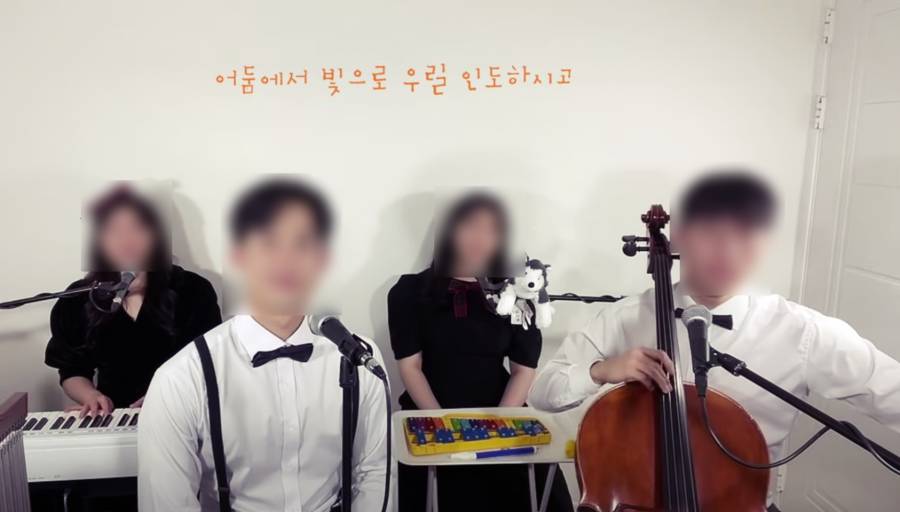
제가 좋아하는 유튜브 채널에서 CCM을 시청하고 있었는데요. 그 노랫말, 가사 글씨가 너무 예쁜 거예요. 갑자기 글씨체, 글꼴이 궁금해졌답니다. 대체 무슨 폰트일까? 호기심이 발동!!! 일단 전체화면을 캡처해 보았습니다.ㅎㅎ
그러고 나서 바로 산돌구름 홈페이지에 접속해 봅니다... 산돌구름 홈 화면 상단 우측에 보면 '키워드나 이미지로' 폰트 검색하는 방법이 있답니다.ㅎㅎ
산돌구름 홈페이지에서 이미지로 폰트 검색을 눌러봅니다...
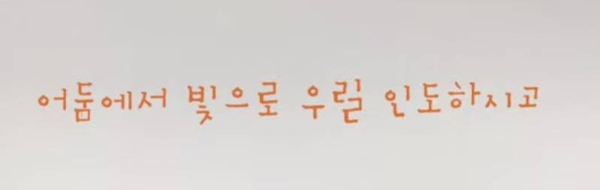
미리 캡처화면에서 글씨들만 따로 편집해 두었답니다.ㅎㅎ 정말 산뜻하고 예쁜 글씨체입니다... 얼른 글씨체 이름을 알고 싶네요.
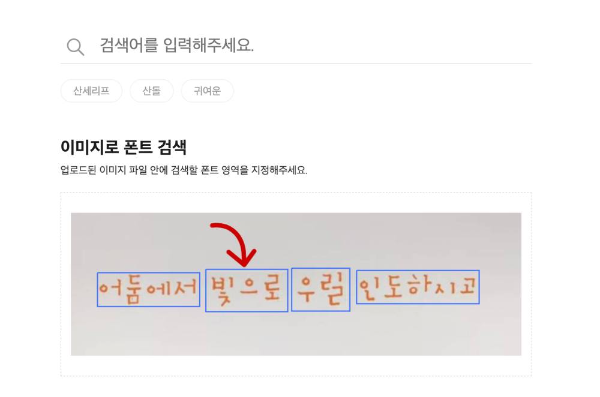
이미지로 폰트 검색에서 검색할 폰트 영역을 지정해 줍니다. 저는 '빛으로' 영역을 클릭해 주었습니다...
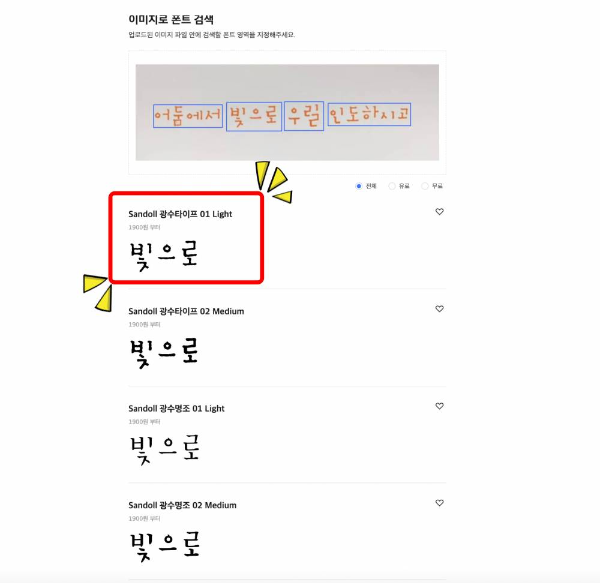
와~~ 얼마 지나지 않았는데 검색이 완료되더니 제가 궁금해하는 글씨체를 나열해 줍니다. 나열되는 글씨체 중에서 제가 찾던 글씨와 맞는 부분은 확인해 볼 수 있는데요. 정확히 일치하는 글씨체를 발견하였습니다. 제가 찾던 글씨체, 글꼴은 바로 '산돌 광수타이프 01'이었네요.ㅎㅎ
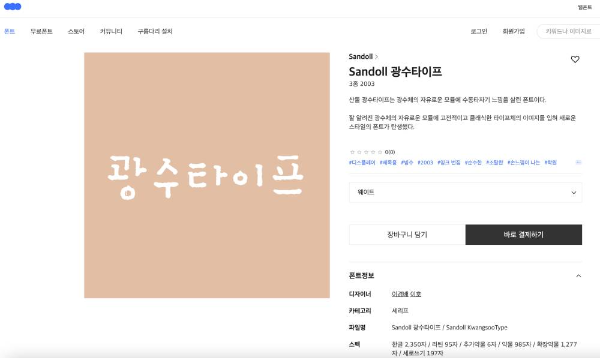
갑자기 폰트 구입에 관한 내용으로 흘러가는데요. 어쨌든 내가 원하는 글씨체를 발견하셨다면 일단 화면캡처 후 그 글씨체 부분만 잘라내기를 통해서 이미지 편집을 마쳐주시고, 산돌구름에서 이미지로 폰트 검색을 하시면 된다는 거 참고해 주세요...